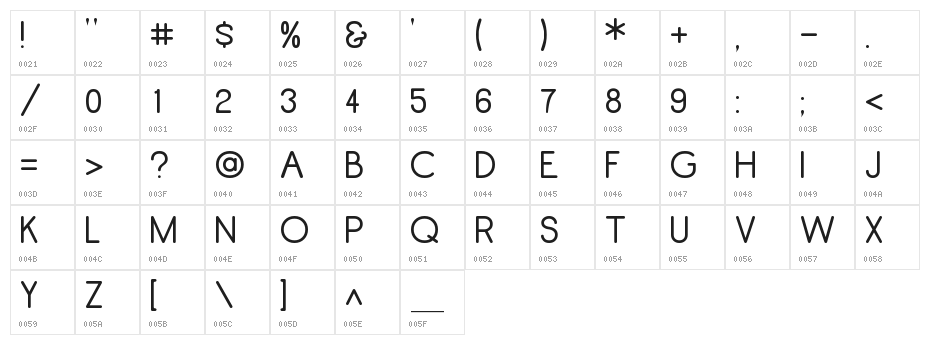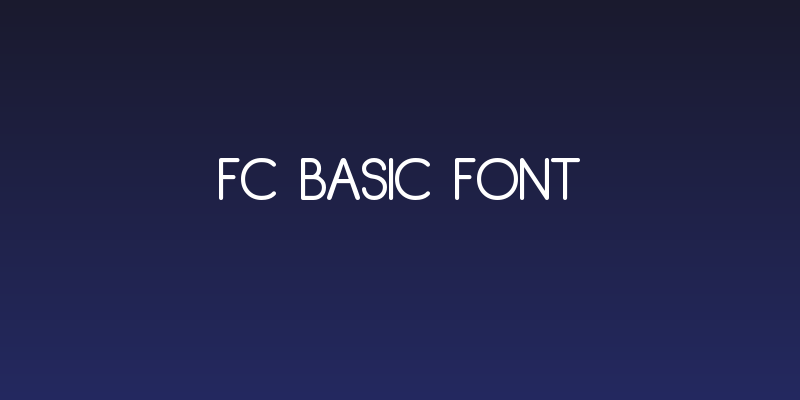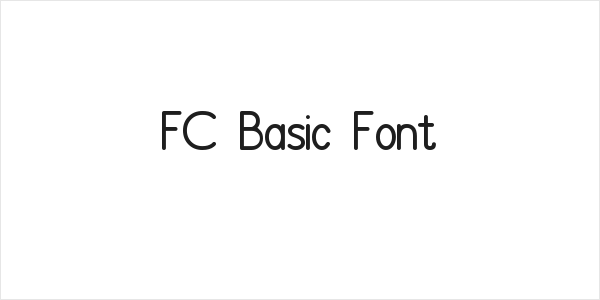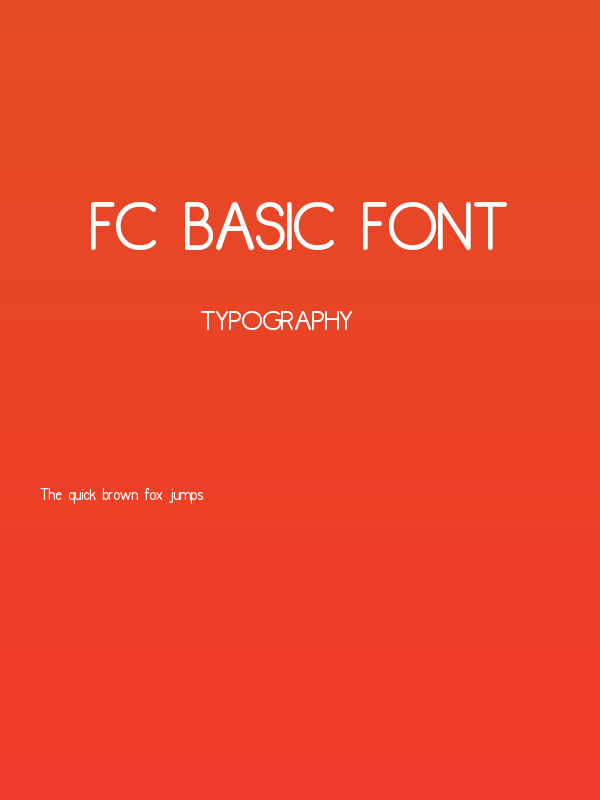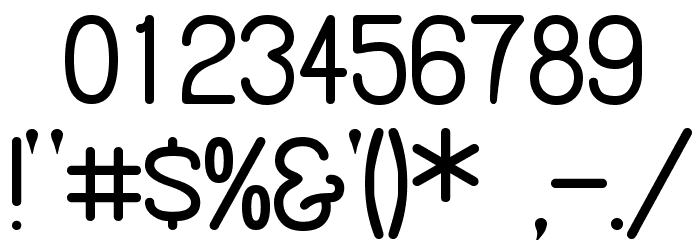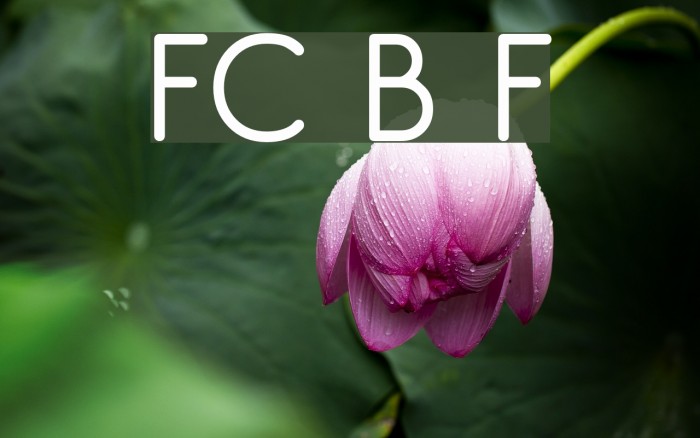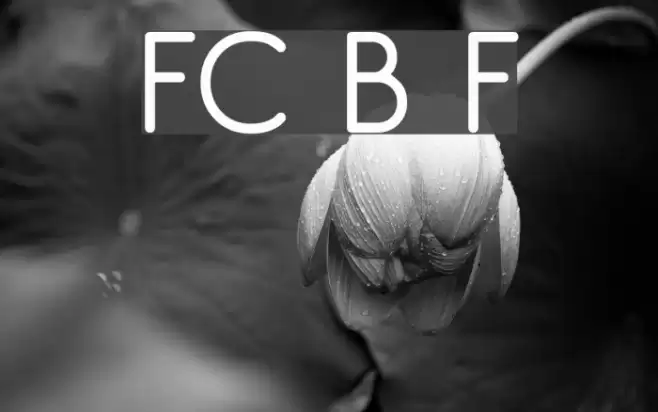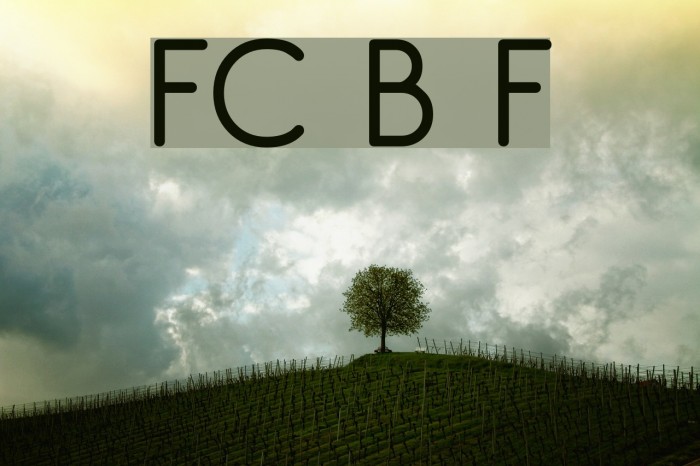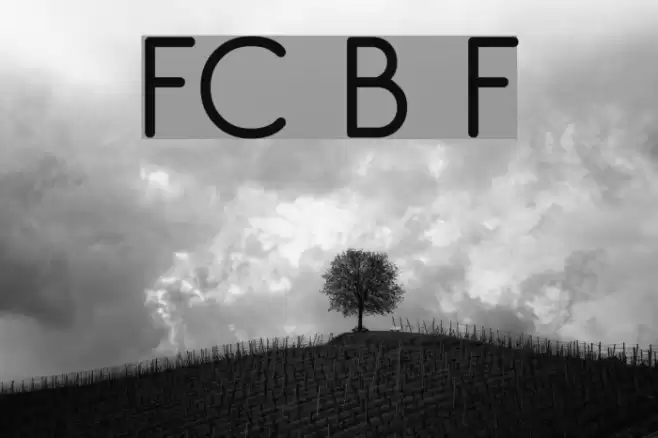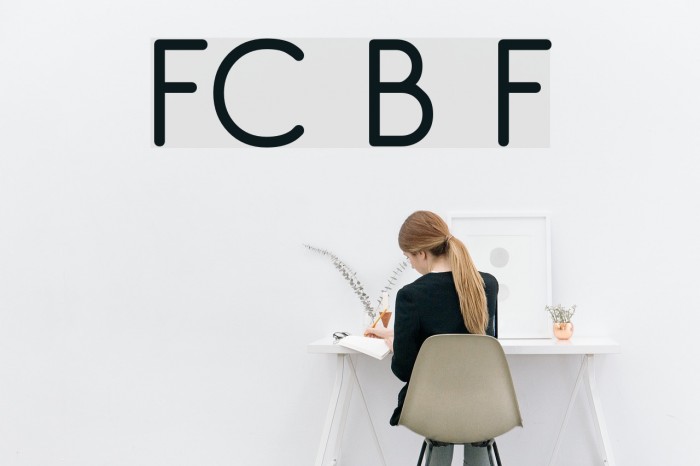
FC Basic Font Font
| Projetos propostos | Ideal for branding, user interfaces, signage, and educational materials due to its clarity and modern appeal. |